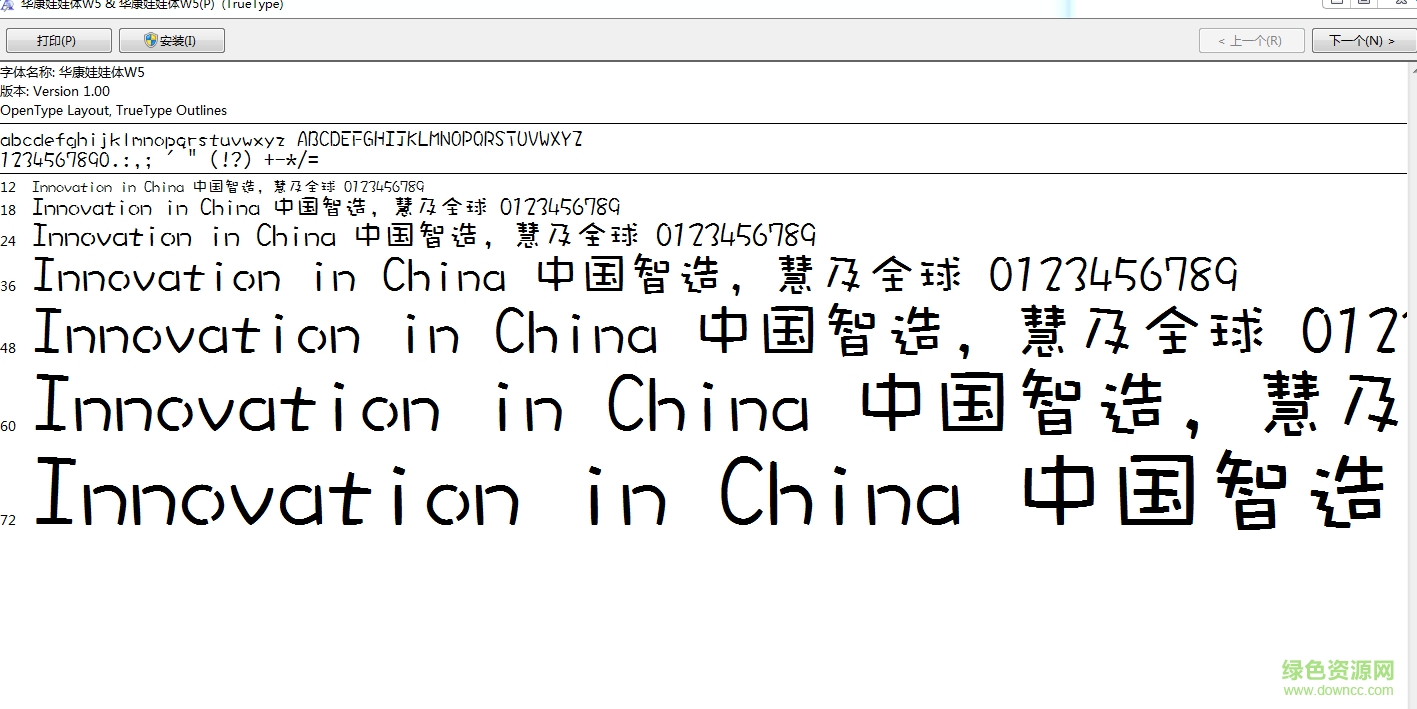
dfwawaw5 regular
dfwawaw5是什么字體?dfwawaw5字體是一款免費的華康娃娃體w5普通字體,該字體活潑秀麗,造型生動,十分好看,適合用于兒童讀物,有需要者歡迎免費下載!
dfwawaw5字體特點
結(jié)構(gòu)密實居中,如橡木酒桶般的筆劃身形,不時可見以短小輕巧的點代替正規(guī)筆劃,或是部首、偏旁間明顯的比例差距,呈現(xiàn)出跳動的字體個性,極富童趣。作為廣告?zhèn)鲉?、兒童書刊、海報及廣告招牌等標題用字相當(dāng)適合。